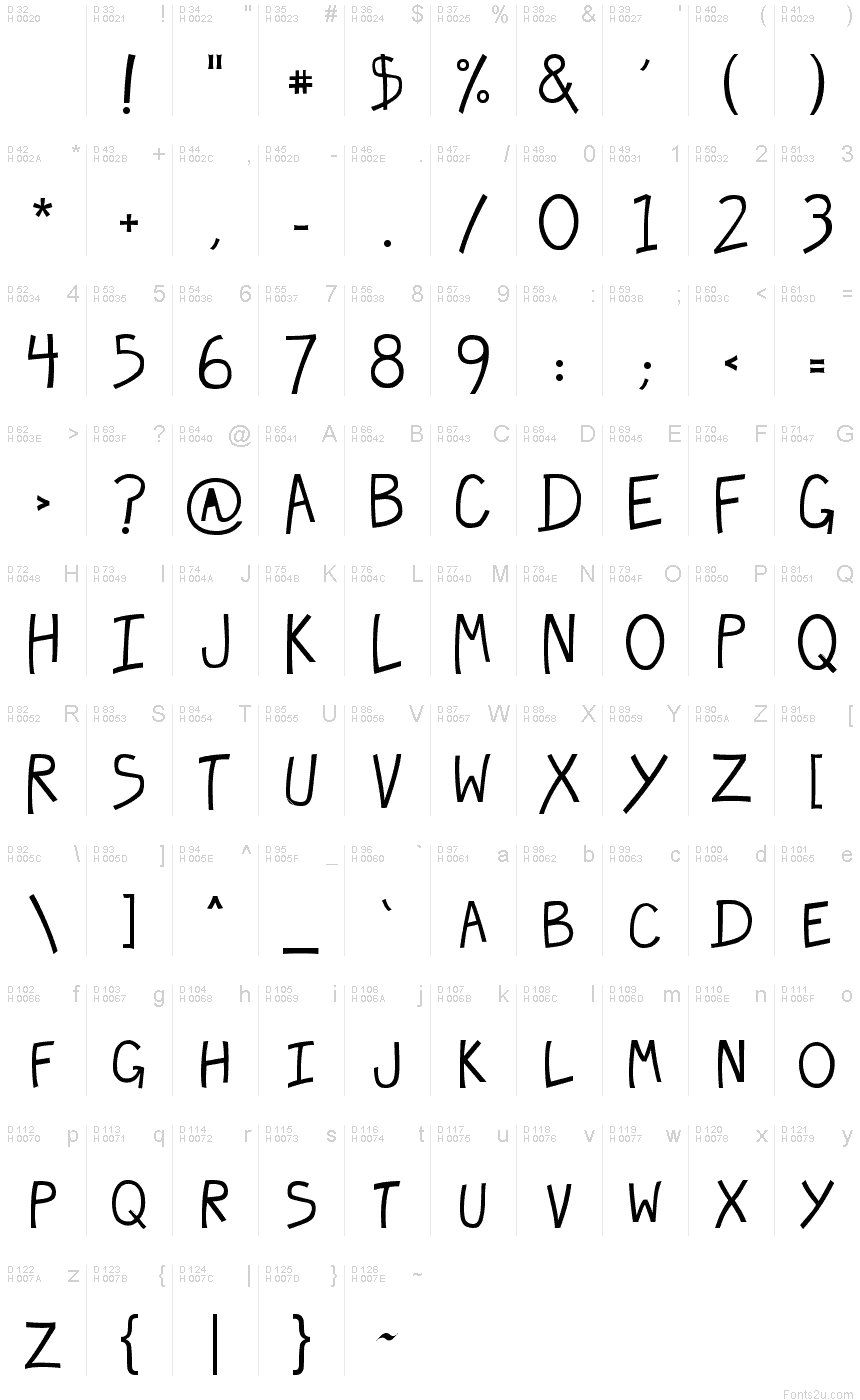
Hecubus od Lauren Ashpole je bezplatné ručně psané písmo. Jeho vysoká, lehce neposedná písmena působí jako rychlé tahy fixou na tabuli – neformálně a lidsky, ale přitom dostatečně čistě na to, aby byla na první pohled čitelná. Úzké tvary a rovnoměrný rytmus vám dovolí vtěsnat i delší nadpisy nebo povídavý text, aniž by působil stísněně. Řeší tak ten častý požadavek na písmo, které je „zábavné, ale přitom čitelné“.
S Hecubus vnesete uvolněný tón do komiksů, fanzinů, školních materiálů, dětského brandingu, plakátů i neformálních obalů. Hladké křivky a vzpřímený postoj udrží vaše sdělení přátelské a přehledné, takže skvěle funguje na obrazovkách i v tisku. Pro jednoduchou kombinaci použijte Hecubus na titulky a doplňte ji běžným bezpatkovým písmem pro drobnější text.